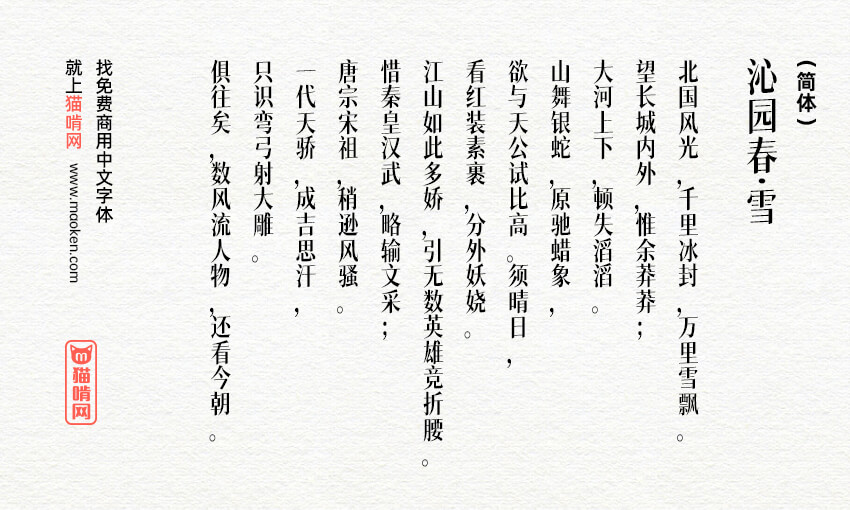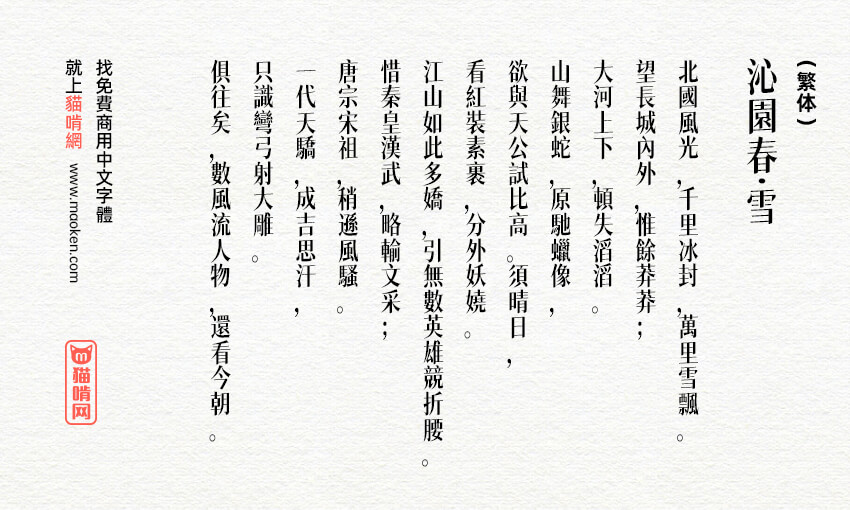
猫啃网风雅宋:基于狮尾四季春改造的宋体字形 免费商用
猫啃网风雅宋是猫啃网网友@新愚公利用业余的时间把狮尾四季春通过程序进行改造,压缩字体宽度,并把字体向上拔高,有点类似仿宋字形。猫啃网风雅宋只有一个字重,采用狮尾四季春SC-Bold。原字体的一些衬线还依然保留。修复过程中发现这些字体基本上用不上,所以没有进行修复,所以有兴趣使用的网友如发现常用字体还有衬线存在的请告知,一定时间内会修复。
Ver 1.30(2025/02/12)
• 修复部分文字错位问题
• 增补了几个字
Ver 1.20(2020/11/28)
• 去除“(‘文’上‘乙’下)、(‘召’上‘乙’下)、(‘可’上‘乙’下)、(‘亠’上‘口’中‘乙’下)、(‘由’上‘乙’下)、(‘老’上‘乙’下)、(‘拘’上‘乙’下)、(‘乳’上‘乙’下)、嚴、望、得、靈、斷、類、種、團、成、體、裂、提、滅、戒、或、重、載、辱、還、標、麗、漂、幢、就、德、定、嗔、慎、填、傎、厧、瞋、嵮、滇、搷、阗、蒖、嫃、缜、縝、寘、槙、瑱、禛、瘨、磌、窴、稹、镇、鎮、颠、顛、衠、謓、蹎、黰、癫、癲、巅、巔、鬒、鷏、攧、齻、真、爱、然、费、費、商、漢、省、院、浣、贫、貧、家、春、者、照、国、略、宽、寬、艳、容、海、侮、悔、梅、霉、诲、晦、酶、酊、酌、配、酎、酏、酐、酑、酔、酕、酖、酗、酘、酙、酚、酛、酜、酝、酞、酟、酠、酡、酢、酣、酤、酥、酦、酬、酪、酩、酮、酰、酯、酧”等字的三角衬线
• 修复上述部分字体笔划异常的问题
• 修复本字体所有问题后,在此基础上未来将增加2个字重,主要加粗字体横笔
Ver 1.10(2020/10/12)
• 修改了“一”的衬线
Ver 1.00(2020/10/11)
• 猫啃网风雅宋第一版正式发布
为什么“一”这样的?,的字没有衬线?
• 带横基本的都很细没有衬线,狮尾B2加糖宋体就没那么细
这个字竖排还可以,但是如果横排的话,字间距比较密,看着累眼睛。
用来做平面设计什么的还行,如果用来阅读,眼睛受不了。
希望可以调整一下字间距,拉开一点。
目前“海”字的对齐还是有问题,非常好看的字体,希望能够有机会修复~
非常棒的宋体!只是竖排标点不符合规范,应该是放在右上角比较好。希望能够修正一下。
使用场景可以对标 小标宋
1.00版,原字体的一些衬线还依然保留,着手修复了以下部分:
一(大写一)
?(“文”上“乙”下)
(“召”上“乙”下)
(“可”上“乙”下)
(“亠”上“口”中“乙”下)
?(“由”上“乙”下)
(“老”上“乙”下)
(“拘”上“乙”下)
(“乳”上“乙”下)
修复过程中发现这些字体肯定用不上,没必要去修复,所以有兴趣使用的网友如发现常用字体还有衬线存在的请告知,一定时间内会修复。